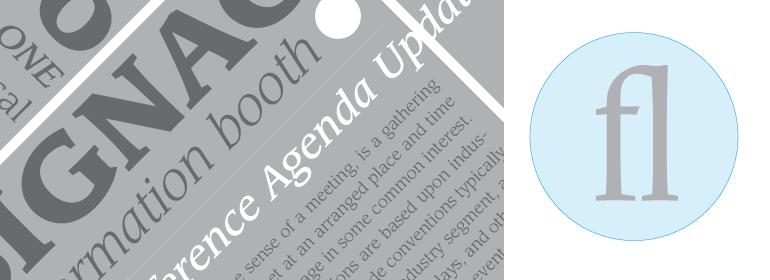
ITC Leawood®
ITC Leawood®,这款字体结构工整、笔画清晰,兼顾美观与易读性,适用于标题、正文、海报、包装、LOGO 等多种场景。字形优雅稳定,风格百搭耐看,适配日常排版与创意设计,让文字呈现更舒适、更具质感。ITC Leawood®一笔一画,皆是细节,以均衡的比例、流畅的线条打造舒适视觉体验,字形端正大气,风格简约现代。无论是商业设计、品牌宣传还是日常排版,都能轻松驾驭,让文字更有格调与力量。ITC Leawood®字体下载。
字体品牌: ITC(Monotype) 设计师:Usherwood,Leslie 字体分类:衬线体 字体属性:外文 字符集:Unicode 发布时间: 2018